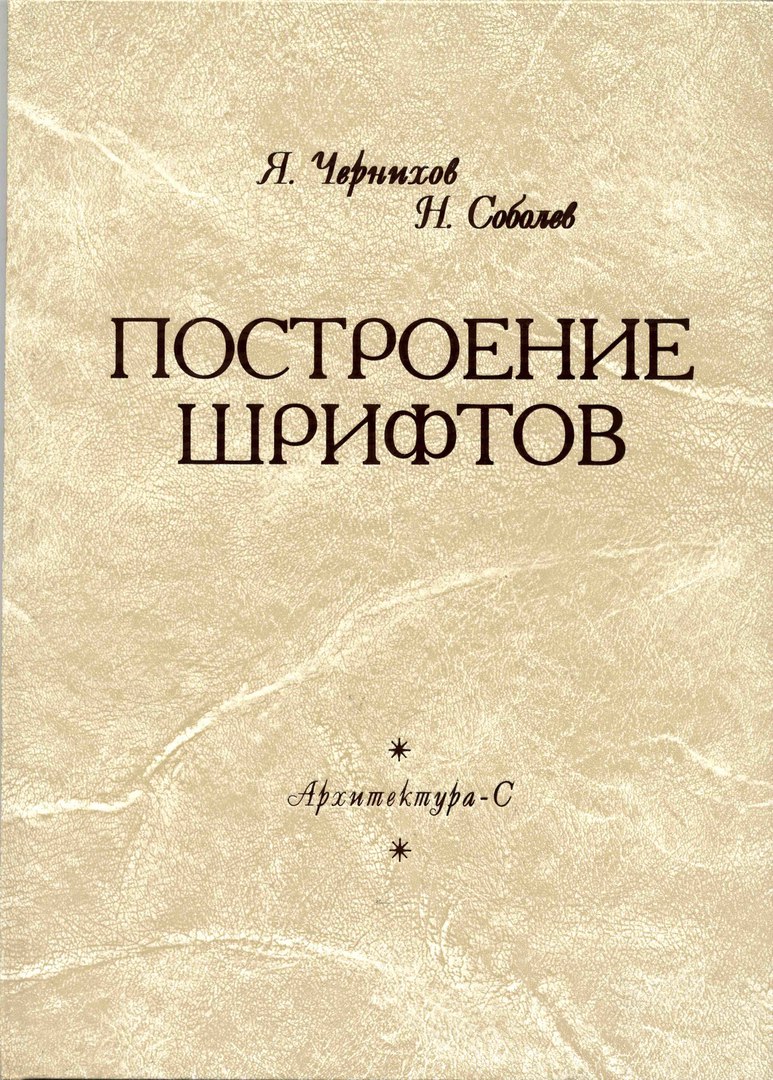
«Построение шрифтов», Чернихов Я.Г., Соболев Н.А.
В предлагаемой читателю книге, кратко освещены теоретические основы шрифтовой графики и изложены правила и приемы воспроизведения шрифтов и надписей. Основное внимание уделено вопросам построения букв.